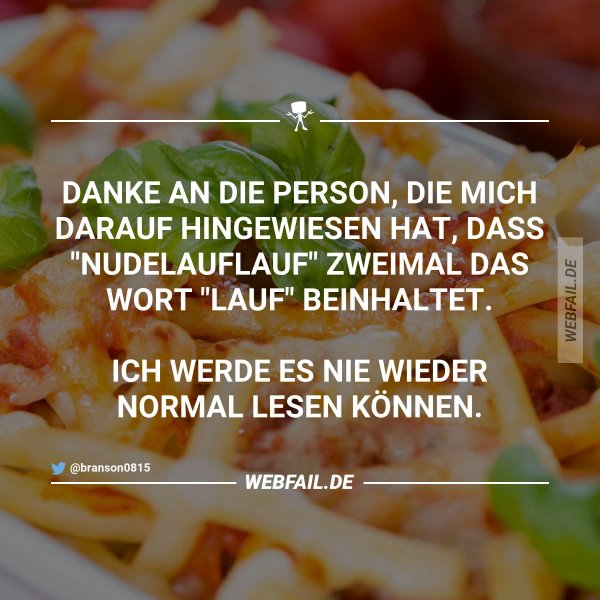
Ich kann den Stadtrat nicht mehr hören :blabla:
Stadtratsharing
Ich habe das mal korrigiert, so wie ich es zuerst lesen wollte, und gehe ihn jetzt mal teilen ...
Notentriegelung  :-)
Das Triegeln von Noten ist ein deutliches Merkmal moderner Avant-Garde-Musik :nicken::roll:
Das Schulzentrum hat bei uns in der Familie eine besondere Bedeutung, seit mein lesenlernender  Sohn mich fragte,  als wir an einem entsprechenden Schild vorbeifuhren: "Papa, was ist eigentlich ein Schulzen-Turm?
Genau in so einer Schrift mit kleinen Ls ohne Schwänzchen und rechtreckigen i-Punkten auf Versalhöhe
Nachbarskater
Stimmt. Martin Z. Schröder war’s damals … :gimmifive:
Zumal man dies sogar kombinieren kann: Nachbarskater hält sich lieber gemütlich in der Wachſtube auf, während der Nachbarſkater eben die Wachstube zur Pflege seines Bords braucht.
Manchmal pflegen die Skater sogar ihr Board, nicht nur das Bord … :tuschel:
Kunstharzestrich -
kommt immer mehr in Mode: Zeichnen mit Kunstharzen. Die feinen Striche, die nach dem Trocknen leicht erhaben sind, werden als Kunstharze-Striche bezeichnet.